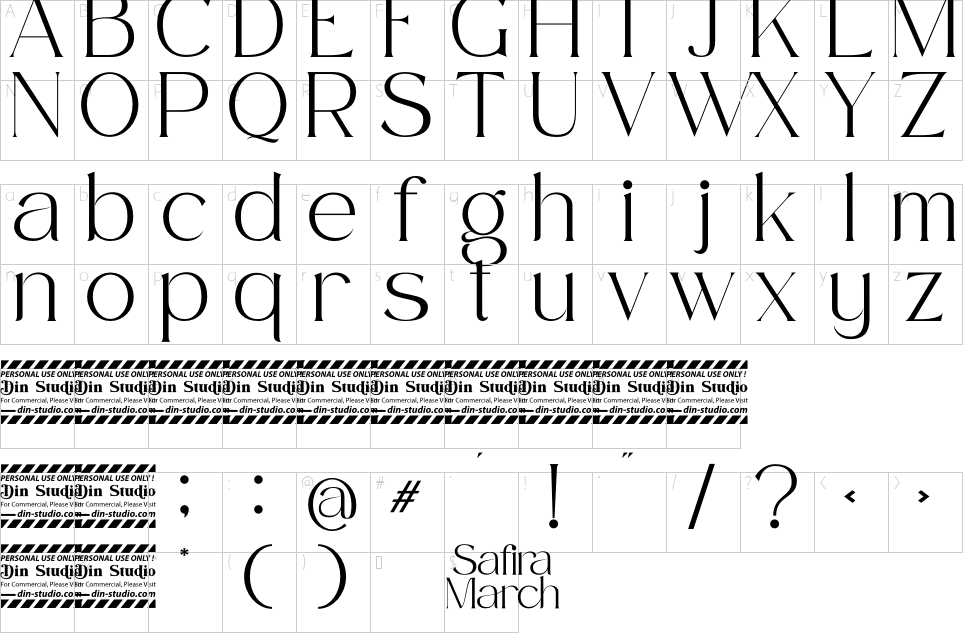
A Safira March é uma fonte elegante e moderna disponível para quem busca aprimorar seu trabalho gráfico. Desenhada por Din Studio, esta fonte vem em versões para Windows e Mac, permitindo que você personalize e personalize seu design digital de maneira atraente. Com sua designação fluida e harmoniosa, a Safira March é uma escolha inteligente para projetos que exigem estilo e elegância. Essa fonte tem se destacado entre os designers, sendo baixada cerca de 6,147 vezes, evidenciando sua popularidade e qualidade. Seja para criar textos legíveis ou trabalhar em layouts elaborados, a Safira March é uma fonte que merece ser explorada.